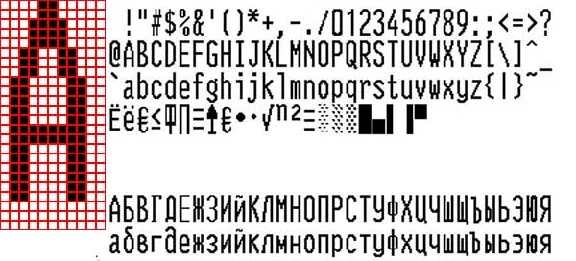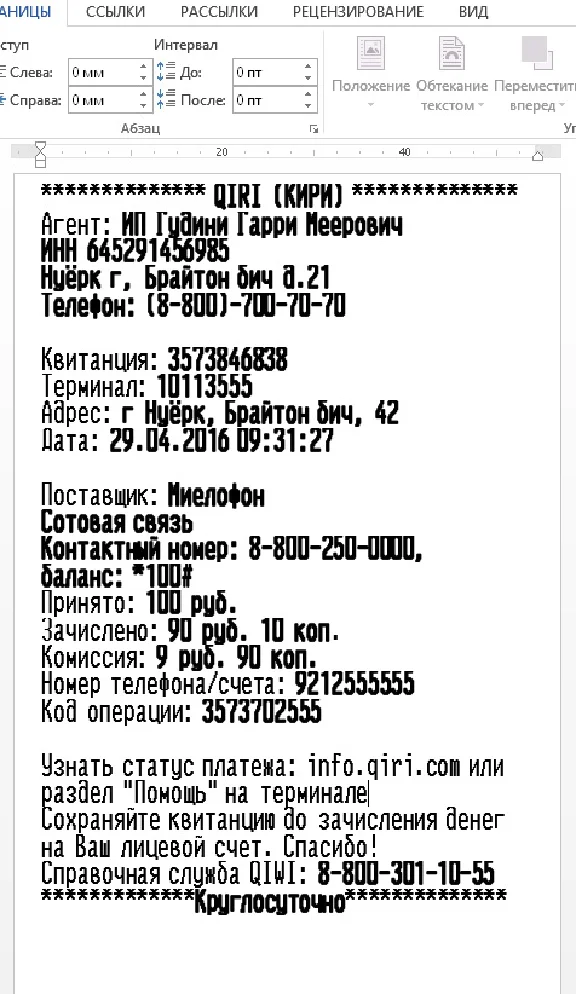
Шрифт терминала оплаты VKP-80, версия 2
True Type (.TTF) шрифт чекового термопринтера VKP-80. Принтер используется в терминалах оплаты и торговых киосках.